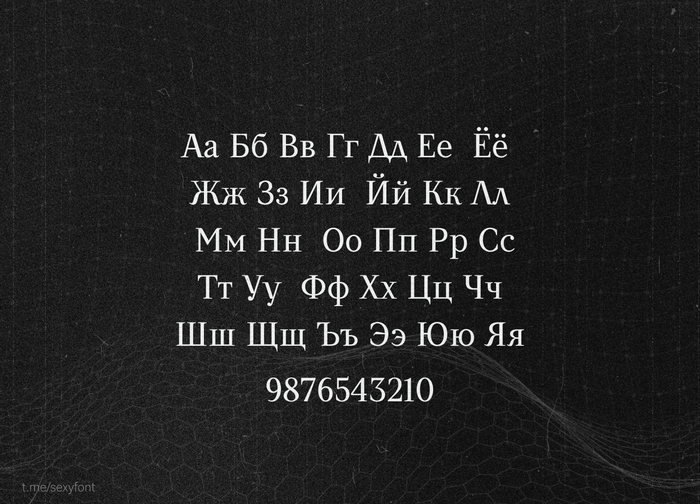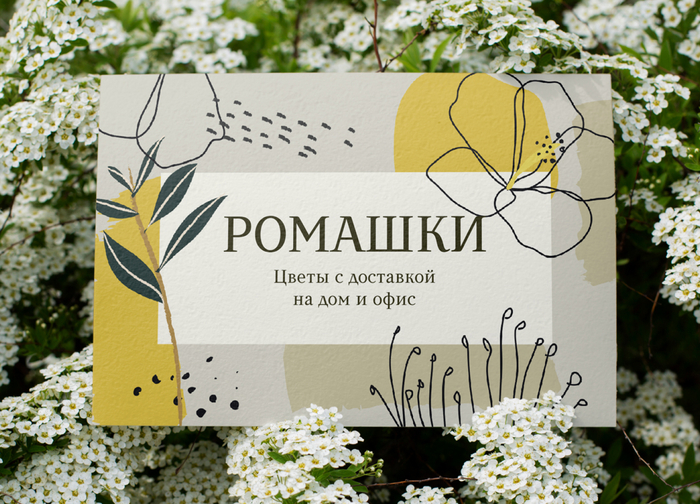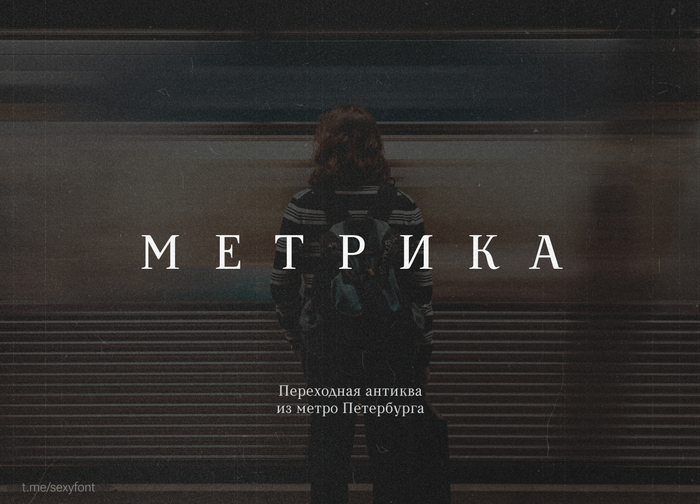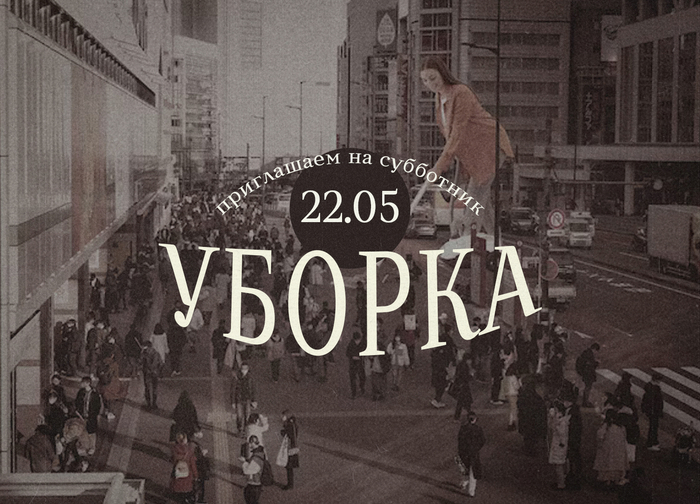
Шрифт Metrika. Бесплатная антиква
От автора:
«Этот шрифт я сделал, как итоговый проект на курсе. С тех пор ничего в нём не менял. И только сейчас решил поделиться. Со всеми наивными ошибками и недоделками. Пусть будет! Итак, встречайте, Метрика!»